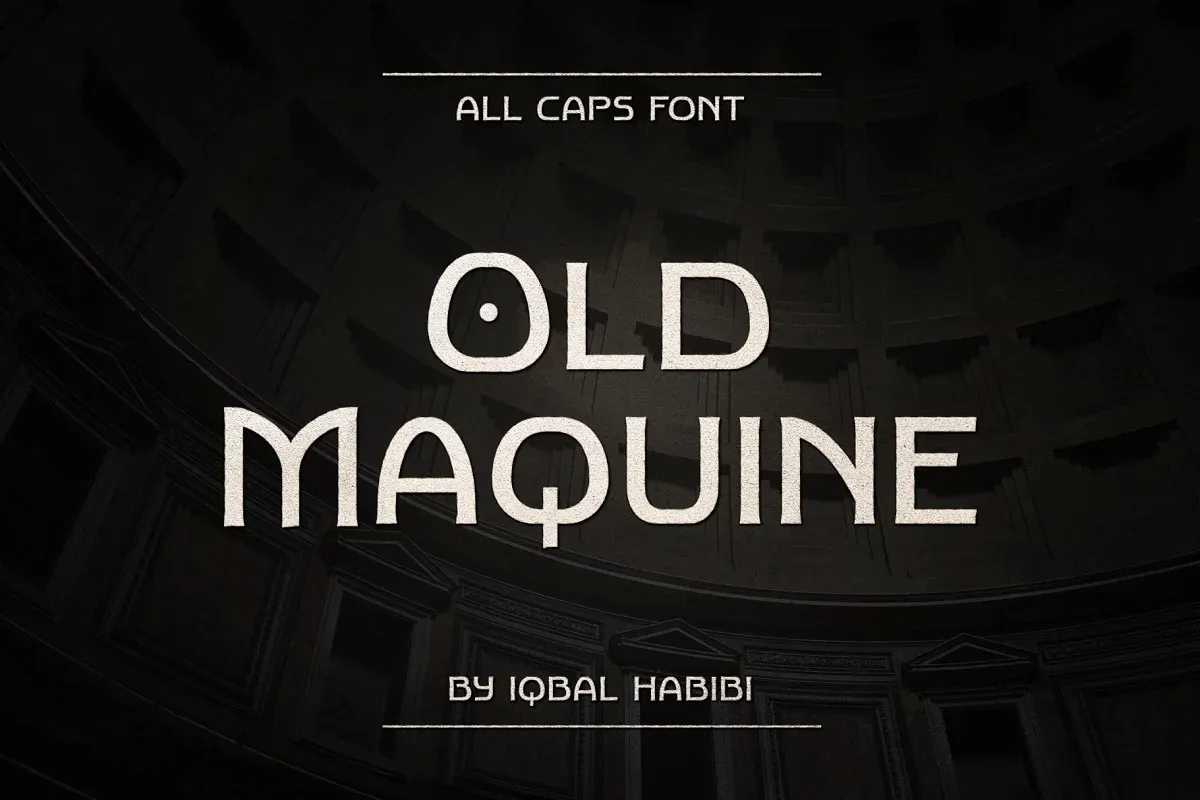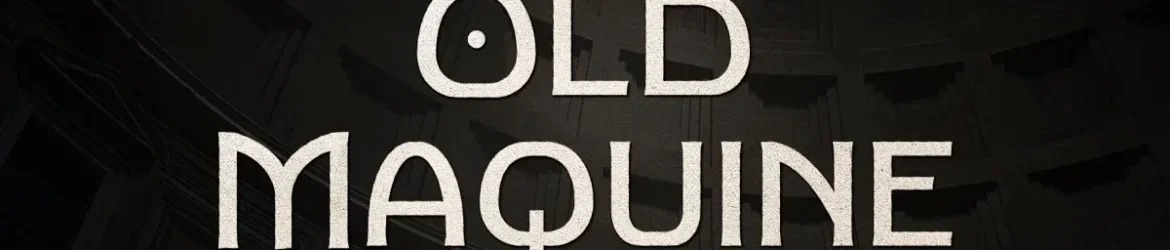
Esta fonte é uma tipografia sans serif ornamental que transmite elegância e clasicidade com um toque vintage, inspirada nos tipos antigos do início do século XX. Old Maquine possui um design limpo e oferece um look autêntico. Ideal para projetos de design variados como capas de livros, camisetas, logotipos, sinalizações e muito mais. Escolha Old Maquine para dar ao seu projeto uma personalidade única e sofisticada.